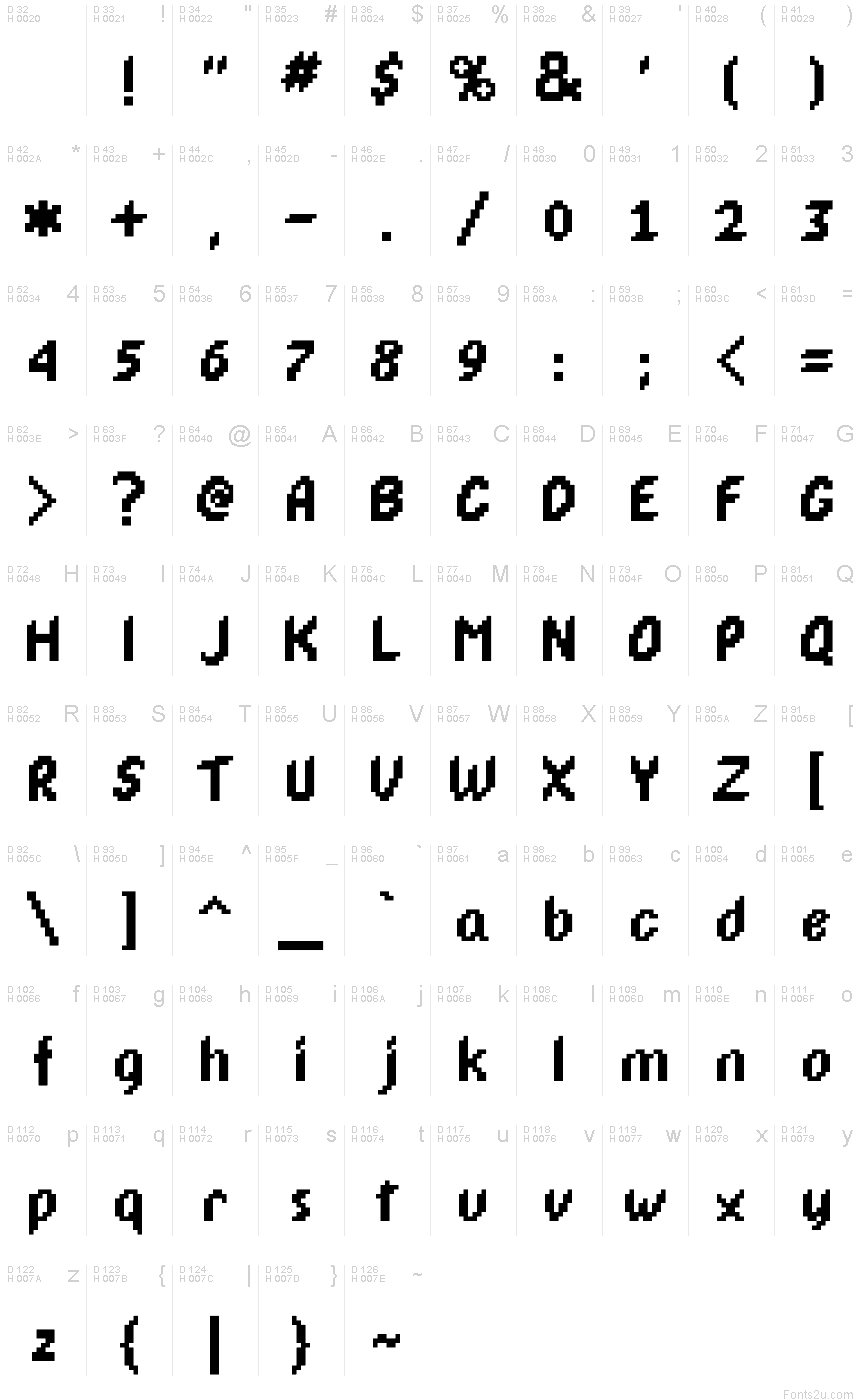
خط DPComic من تصميم Codeman38 هو خط نقطي (Bitmap) مجاني. تم بناؤه على شبكة دقيقة مع منحنيات عريضة ومتدرجة، مما يجعل كل كلمة تبدو وكأنها مقتبسة من شريط قصص مصورة بأسلوب 8-بت. الحروف تبدو طويلة وحيوية وليست جامدة أو ثقيلة، مما يمنح عائلة خطوط DPComic طاقة ودودة وجذابة على الشاشة.
باستخدام خط DPComic، ستحصل على نصوص تبرز بوضوح في واجهات الألعاب الكلاسيكية، ومربعات الحوار، وقصص الـ "بيكسل آرت"، وتراكبات يوتيوب أو تويتش، وعناوين المواقع ذات الطابع النوستالجي، والشعارات التي تشبه الملصقات. هذا الخط المجاني يتألق حقاً عند استخدامه بأحجام كبيرة حيث يمكن تقدير كل بكسل؛ وللنصوص الأساسية، يُفضل تنسيقه مع خط "بيكسل" أحادي المسافة بسيط للحفاظ على سهولة القراءة والتناسق.